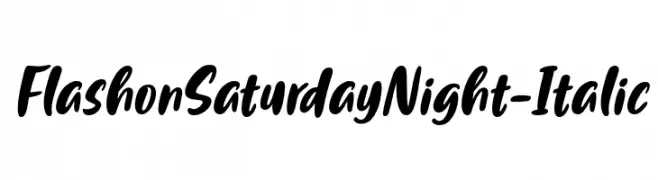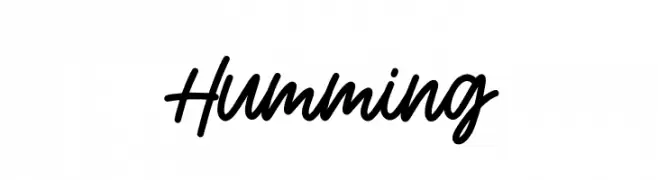
A lively, flowing script font with smooth, connected strokes.
A bold, italicized font with a modern and dynamic style.
A playful, casual handwritten font with smooth curves and a friendly appearance.
A graceful, flowing script font with elegant, connected characters.
An artistic, sketch-based illustrative font with unique drawings for each character.
A decorative font with glyph-like symbols resembling ancient hieroglyphs.
A bold, futuristic font with geometric and consistent strokes.
A bold, italicized handwritten font with a lively and dynamic style.